Khi thiết kế slide PowerPoint, đặc biệt là các thầy giáo, cô giáo muốn thiết kế slide bài giảng, việc sử dụng nền slide bảng đen với nội dung được trình bày theo font chữ phấn viết bảng sẽ giúp slide sống động, gần gũi và sáng tạo hơn rất nhiều đó. Trong bài viết này, Gitiho sẽ chia sẻ với các thầy cô giáo và các bạn 21+ font chữ phấn viết bảng đẹp nhất để sử dụng trong thiết kế slide nhé!
Dưới đây là 21+ font chữ phấn viết bảng với những nét viết, kiểu dáng khác nhau, bạn có thể tải xuống và lựa chọn sử dụng sao cho phù hợp với slide của mình. Bạn có thể tải các font chữ này ở cuối bài viết nhé!
Lưu ý: Vì font chữ phấn viết bảng đều là font chữ sáng tạo, cách điệu, vì vậy nên bạn nên dựa vào độ dày và liền mạch của nét chữ, cũng như độ dễ đọc hay khó đọc để lựa chọn font chữ cho phần nội dung chính hoặc tiêu đề, đề mục cho phù hợp
Font chữ DK Crayon Crumble: Nét mảnh, thích hợp để làm font chữ cho phần nội dung chính của slide
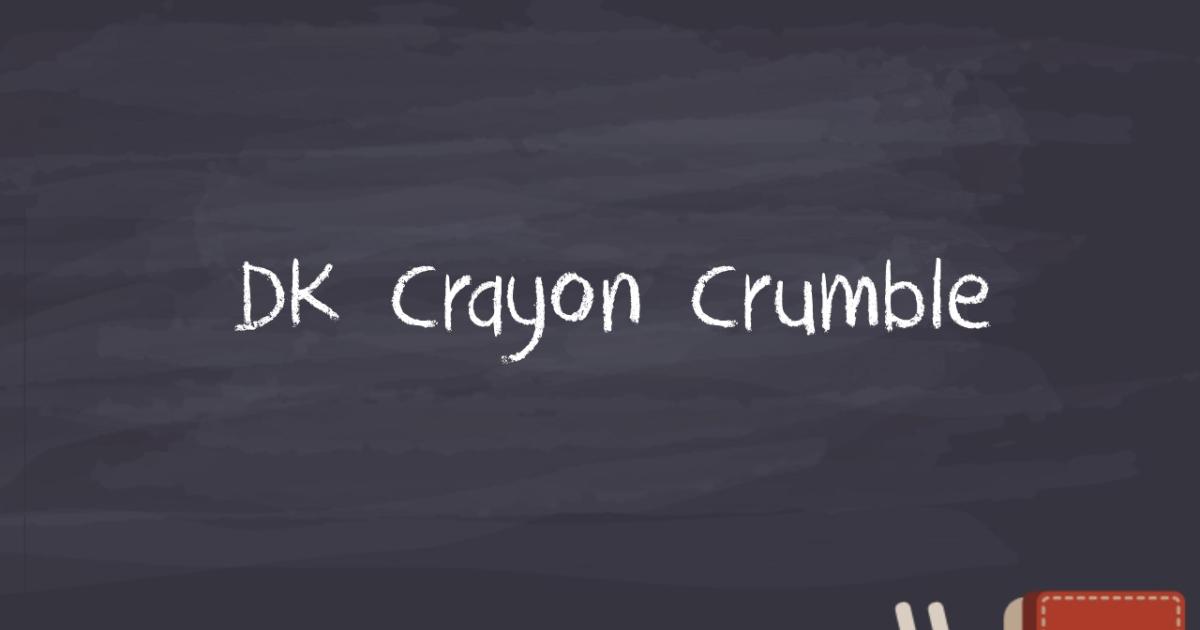
Font chữ ERASER: Các nét không liền mạch, khá dày, nên để cỡ chữ to và sử dụng làm các phần tiêu đề, đề mục
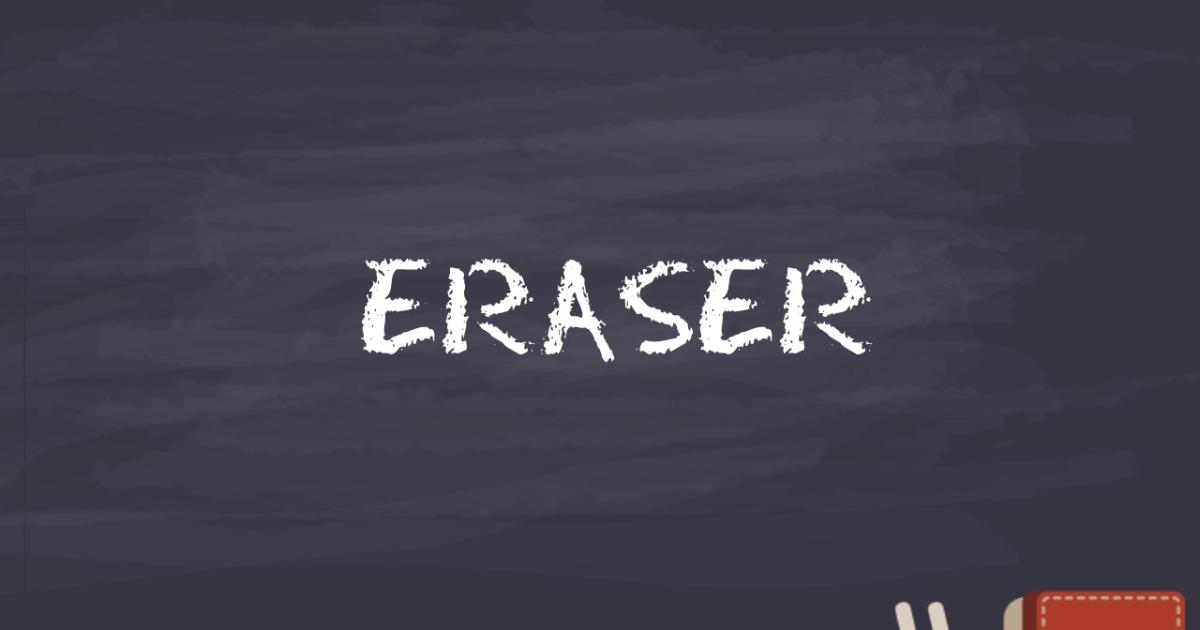
Font chữ PencilPete: Nét mảnh, thích hợp để làm font chữ cho phần nội dung chính của slide
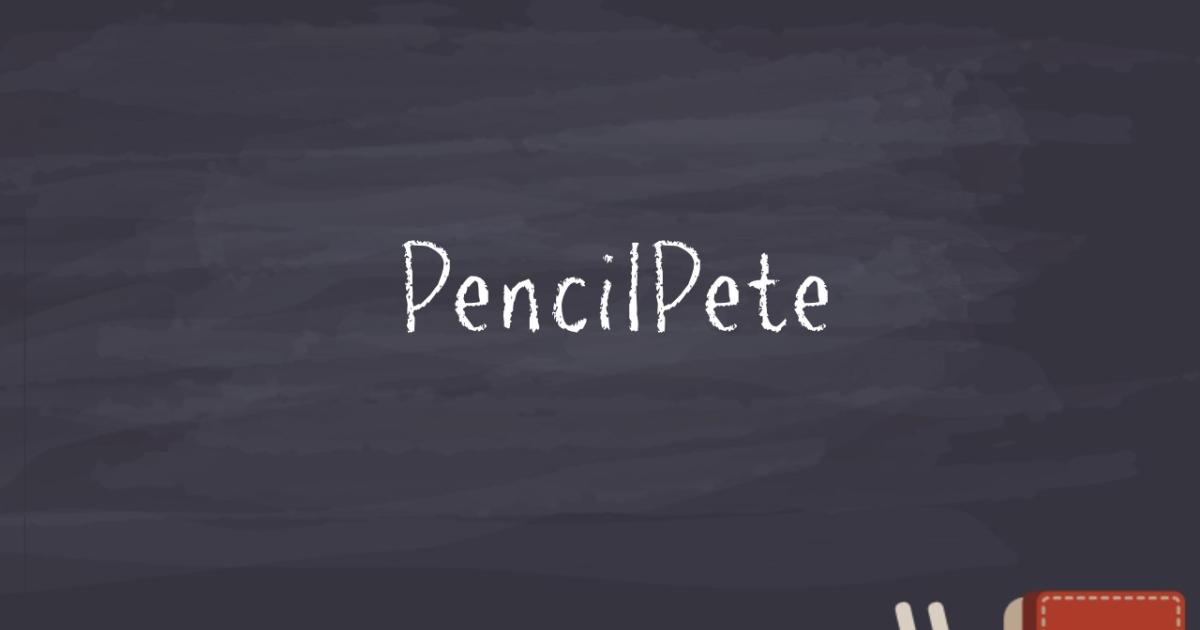
Font chữ Drawing Guides: Nét chữ dày, thích hợp làm tiêu đề, đề mục
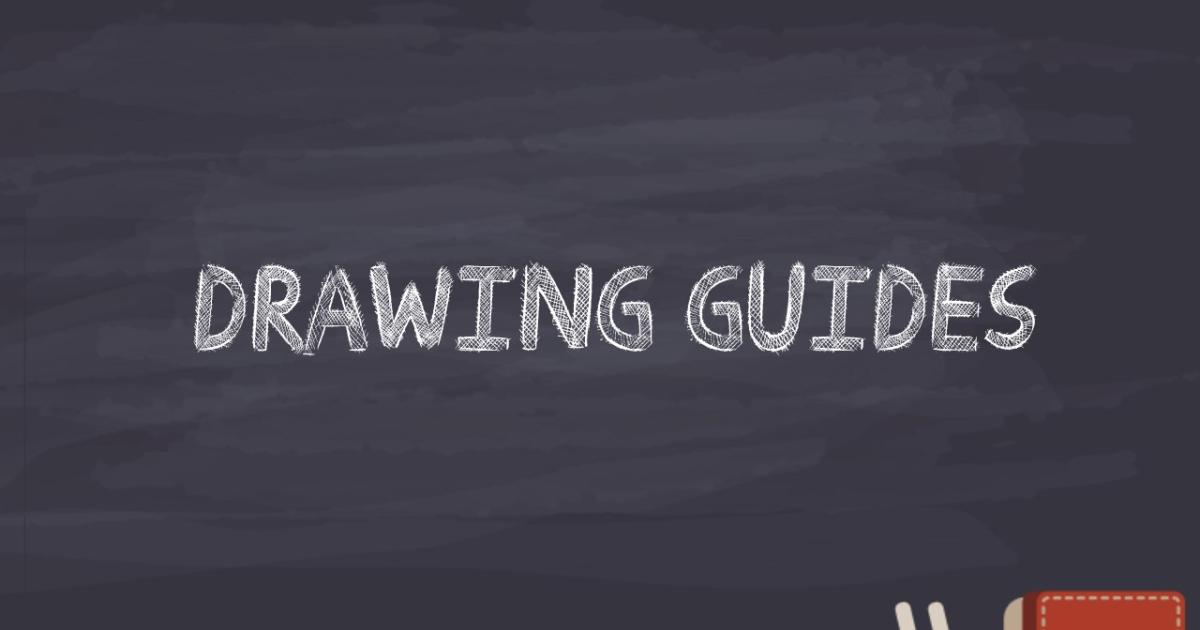
Font chữ Colored Crayon
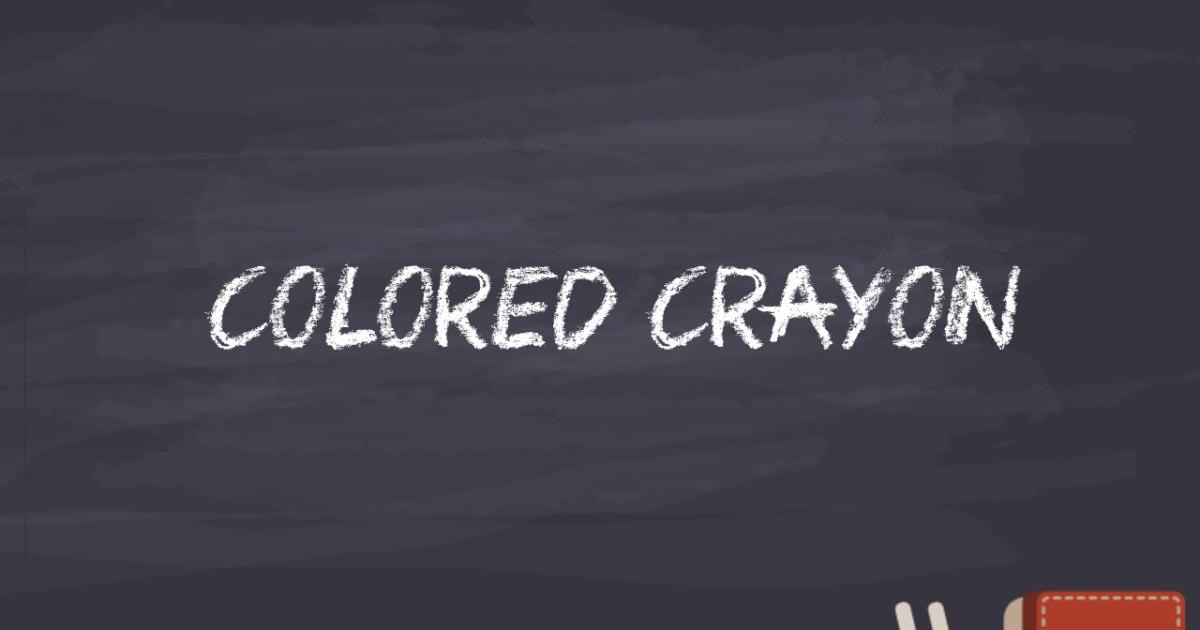
Font chữ Rudiment
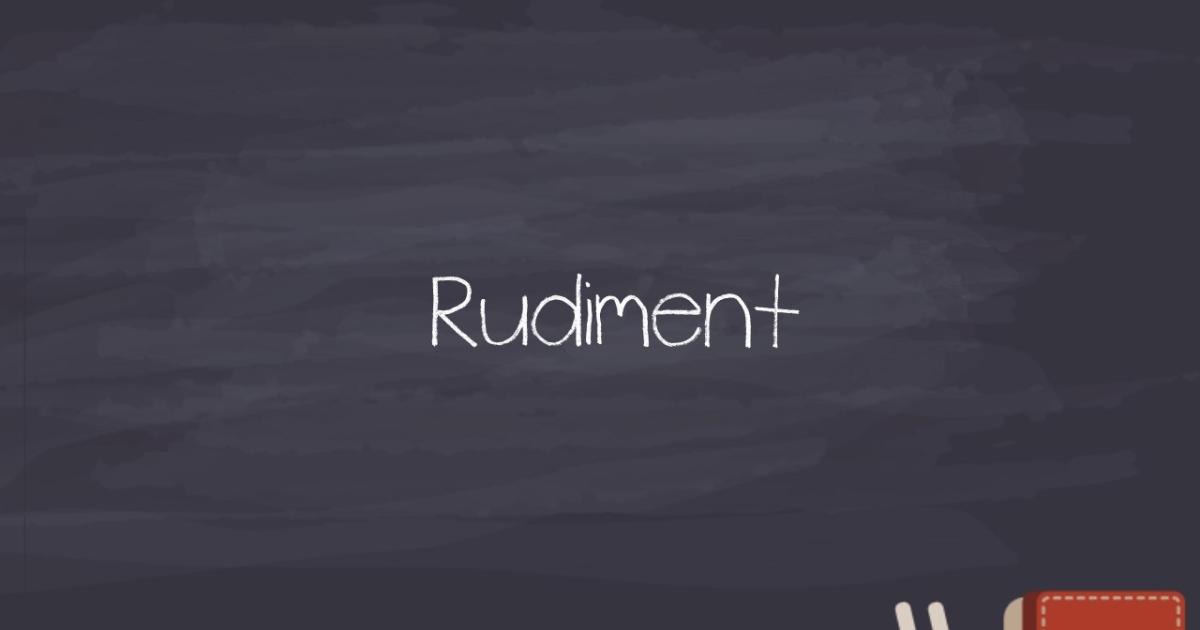
Font chữ Whatever it takes
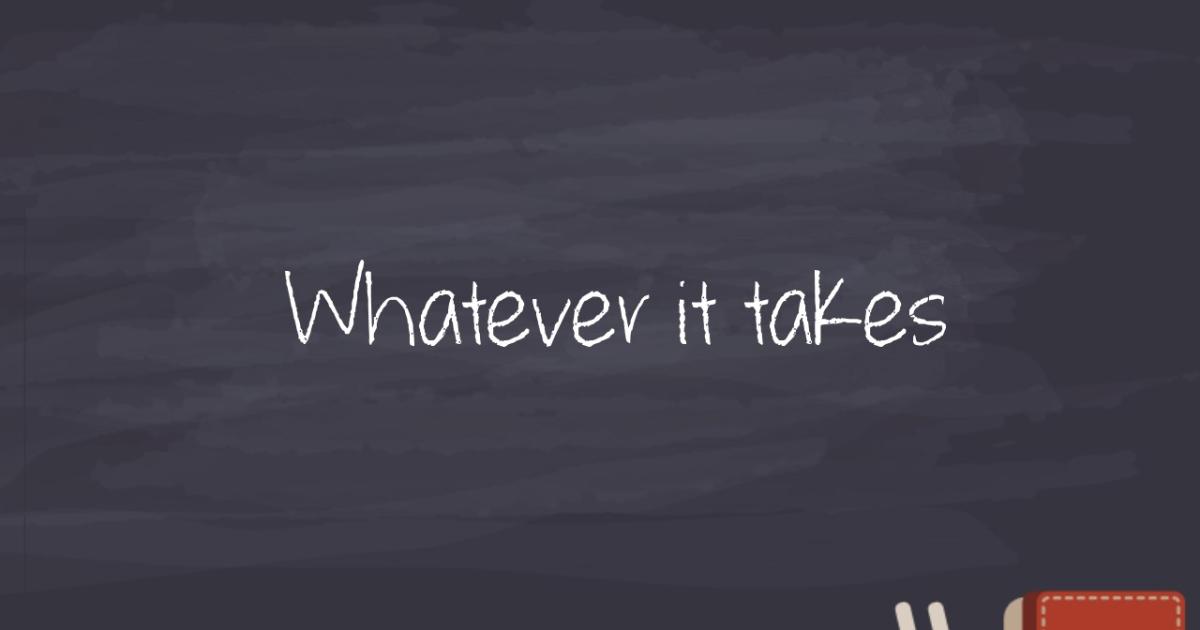
Font chữ Smudgie crayon
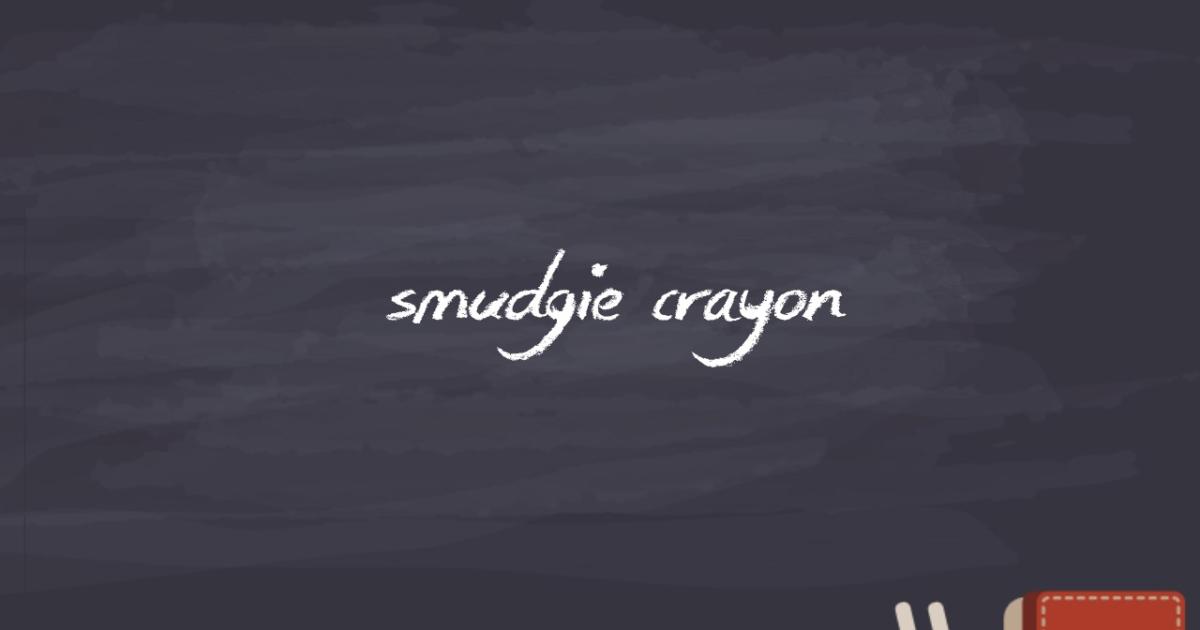
Font chữ Chalkline Outline
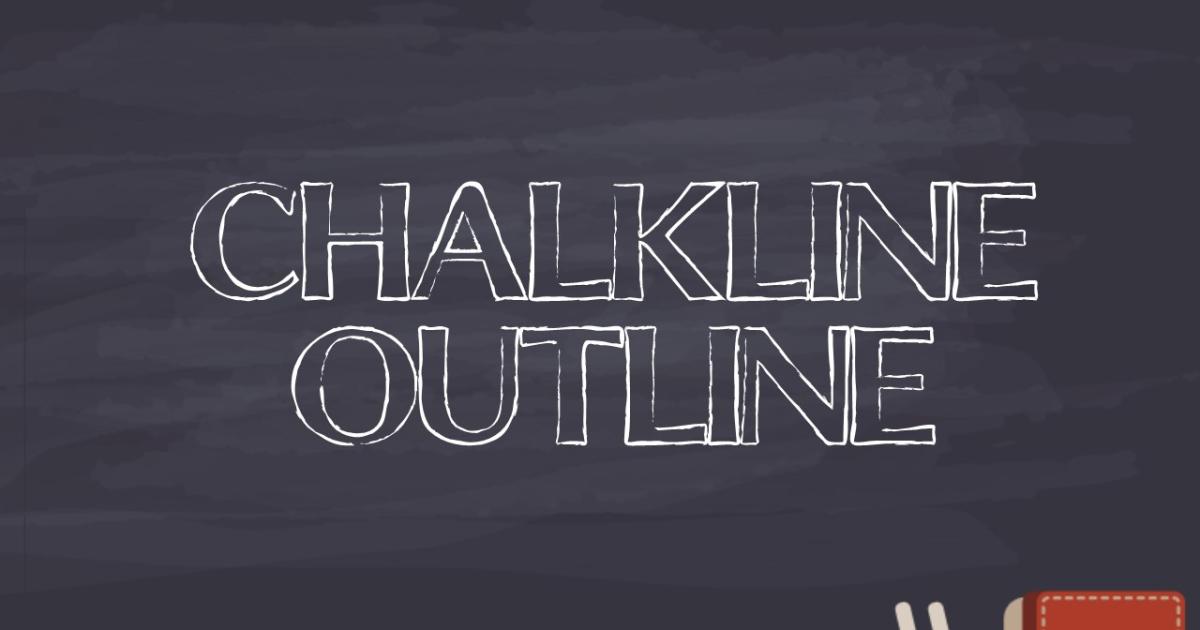
Font chữ Mskitokilla
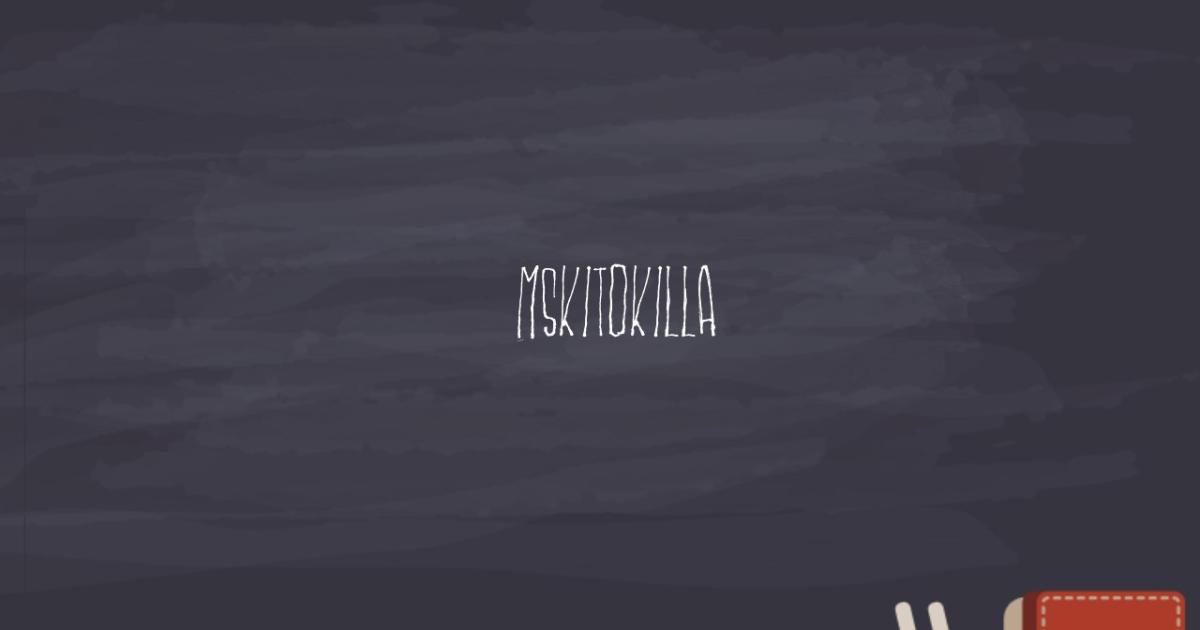
Font chữ Rob Graves
Fotn chữ Chalk Hand Lettering Shaded
Font chữ KG Ten Thousand Reasons
Font chữ Chalkboard
Font chữ Clouds of Despair
Font chữ Urban Sketch
Font chữ Rechtman
Font chữ Return to sender
Font chữ Grutch
Font chữ KG Second Chances
Font chữ FFF TUSJ
Font chữ Eraser Head